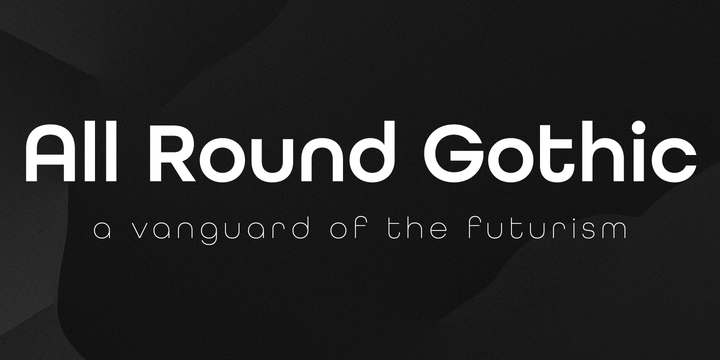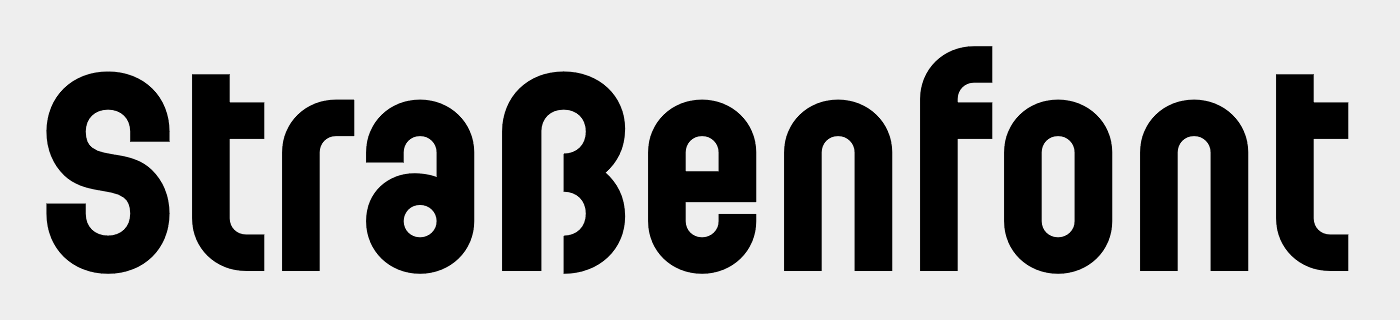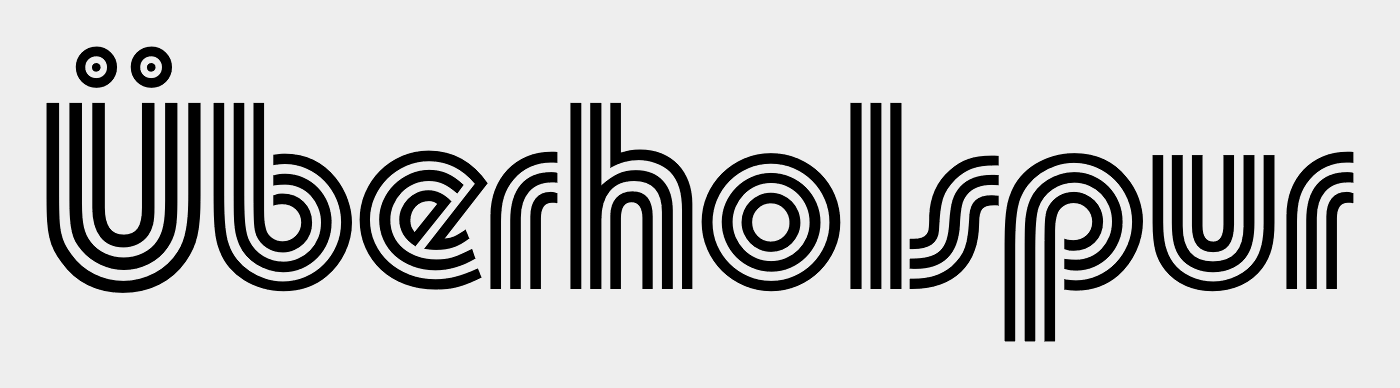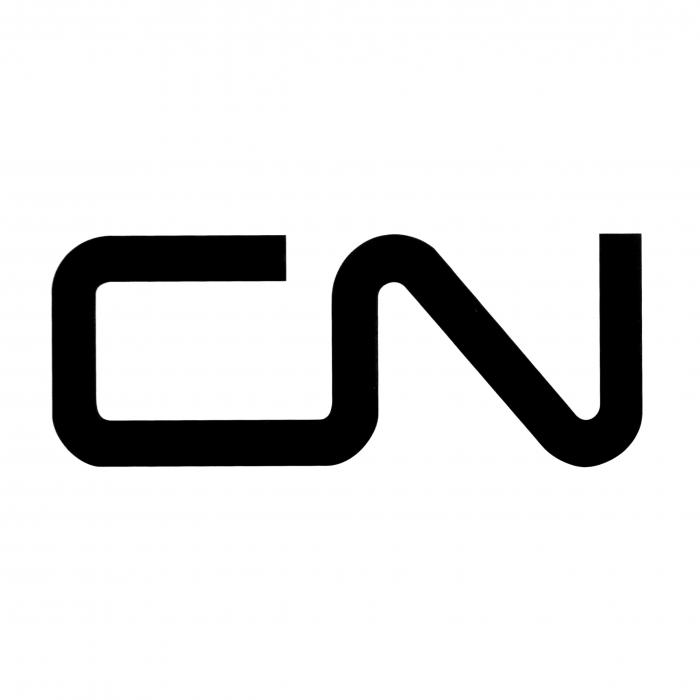
Schrift für Auto-basierten YouTube-Kanal
kurz zu mir: Ich bin 24 Jahre junger Student und plane demnächst einen YouTube Kanal zu eröffnen, der sich vor allem auf Autos und schöne Straßen konzentrieren soll.
Da ich sehr konkrete Vorstellungen bezüglich eines Logos habe, engt das die Auswahl an Schriftarten sehr ein. Wichtig sind mir folgende Punkte:
• Das kleine r soll aus einer Linie bestehen und wie eine Kurve aussehen, also ohne die abstehende Nase links oben. Im Endeffekt soll dieses r auch das Logo bilden, ggf. mit ein paar Ergänzungen.
• Insgesamt soll die Schrift sehr solide wirken, also eher eine größere Strichstärke aufweisen.
• Am besten erinnert jeder einzelne Buchstabe (oder auch die Kombination) an eine Straße, also geschwungen, kaum Ecken, teilweise geradlinig und nichts zu Verschnörkeltes.
Eigentlich hatte ich mich schon ziemlich stark auf Audiowide eingeschossen, nur fehlt mir dabei etwas der Schwung, geht aber sonst schon sehr stark in die Richtung was ich suche.
Natürlich lasse ich mich auch gerne auf alternative Ideen ein, wichtig ist mir wie gesagt ein solides, wenn auch nicht zu ernstes Aussehen, das an eine Straße erinnert. Die Schrift soll vorerst allein fürs Logo dienen, muss also nicht im Fließtext super lesbar daherkommen, wäre nur so ein "nice to have" ;)
Eigentlich hatte ich mich schon ziemlich stark auf Audiowide eingeschossen, …
… welche so aussieht, damit sie nicht jeder aufs Neue suchen muss:
Für dein Logo wäre es eine gute Idee ein Monogramm zu entwerfen. Das passt dann auch gut in die Youtube Vorgaben (quadratisches Bild als Kanalavatar).
Das ist übrigens das Logo (bzw. dessen Schwarz-Weiß-Version) der Canadian National Railway. Nur mal so als Kontext für jene, die keine nordamerikanische Bahnstrecke in der Nähe haben …
Vielen Dank für eure Hilfe, ich spiele die kostenlosen Varianten durch, das Geld geht momentan fürs Equipment drauf. Besonders gut gefallen haben mir die Chalet Schriftarten (1970er und Tokyo).
Ein Monogramm ist auch eine schöne Idee, lässt sich nur mit dem Namen (Curve) nicht so leicht vereinen. Wollte den Namen noch nicht verbreiten, aber was kann schon passieren. Habe mir vorgestellt, dass das 'r' dann als einzelne Kurve, farblich hervorgehoben, ein einfaches Logo darstellen könnte.
Sporn- und Serifenlos sind genau die Schlagwörter die ich brauche, vielleicht finde ich darunter noch etwas :)